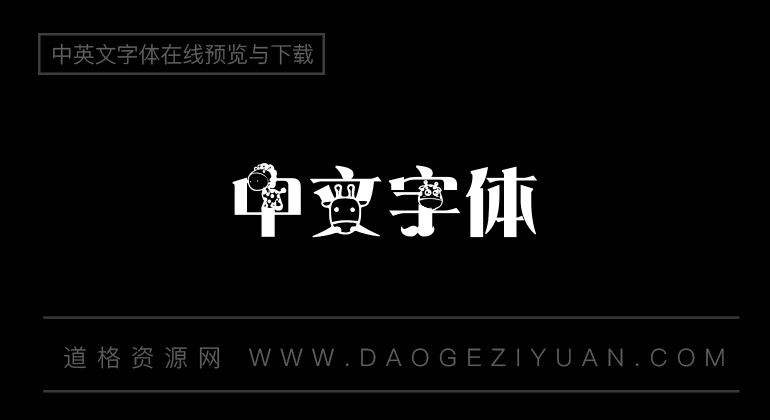
長頸鹿連萌是一款比較特別的字體,它有著非常獨特的風格,類似於長頸鹿的頭部,在字體中有著柔和的曲線,給人一種溫柔可愛的感覺。它有著細膩的線條,讓人一看就愛上它。它適合用於婚禮和派對的賀卡,也適合用於宣傳單上,因為它有著非常獨特的外觀,可以讓人們一眼就能記住。內容介紹
長頸鹿連萌是一款非常不錯的手寫藝術字體,具有很好的視覺感,適合於文化類的宣傳設計、商業類品牌的廣告和產品包裝設計以及個性化文字排版等較多場景。